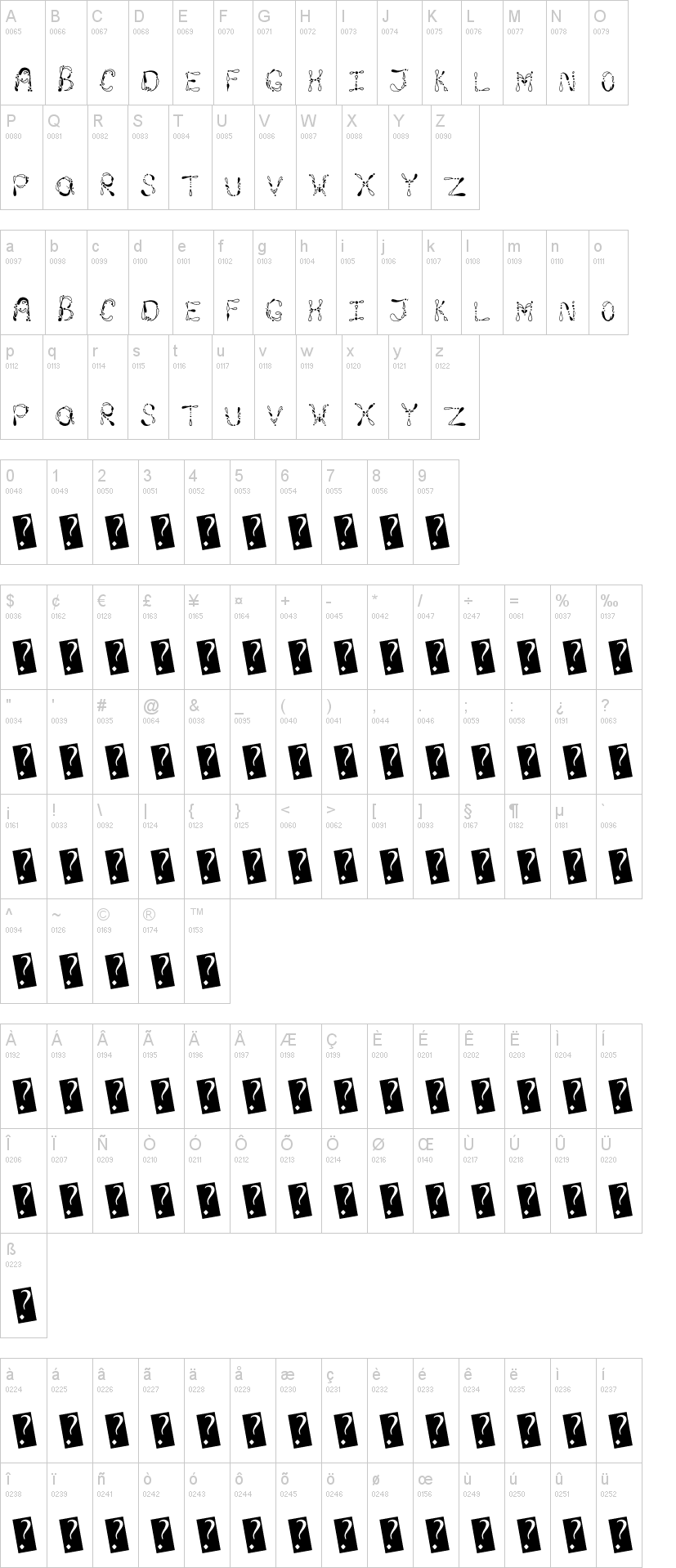
Lube Splash 是一款多功能的字体,由著名的设计师 David Berlow 创作。它的特点是柔和的线条,拥有细节丰富的字体结构,可以在大小、字体重量、字母间距等方面进行调整。Lube Splash 的字体风格灵活,可以应用于各种不同的设计中,包括报纸、海报、海报、书籍、商标等。它的特点是可以根据不同的设计需求进行调整,以满足不同类型的需求,比如可以根据空间限制调整字体大小,以及根据字体重量调整字母间距等。内容介绍
Lube Splash是一款非常不错的手写艺术字体,具有很好的视觉感,适合于文化类的宣传设计、商业类品牌的广告和产品包装设计以及个性化文字排版等较多场景。